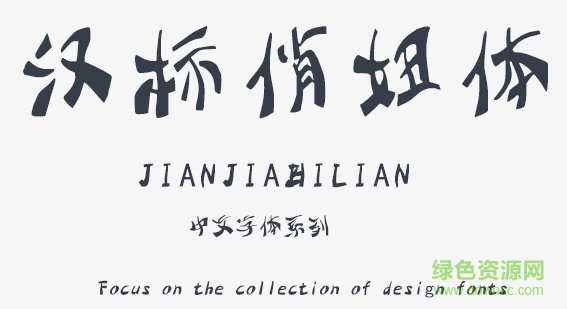
漢標俏妞體字體
漢標俏妞體是漢標公司全新推出的一款造型可愛、結(jié)構(gòu)疏散的中文字體,每個文字均有著歪歪扭扭的造型,給人十分憨態(tài)可掬的視覺體驗,更能吸引讀者的注意,綠色資源網(wǎng)誠意推薦!
漢標俏妞字體特色
漢標俏妞體造型典雅而利落,結(jié)合了圓潤和筆直的線條特色,給人流暢干凈的造型之美,讓你的海報設(shè)計、廣告策劃、藝術(shù)創(chuàng)作更顯獨特品味。
俏妞體
漢標俏妞體是一款適合廣告海報藝術(shù)設(shè)計的字體,字庫完整,支持中英文、繁簡體輸入,能滿足廣大設(shè)計師們的日常需要。